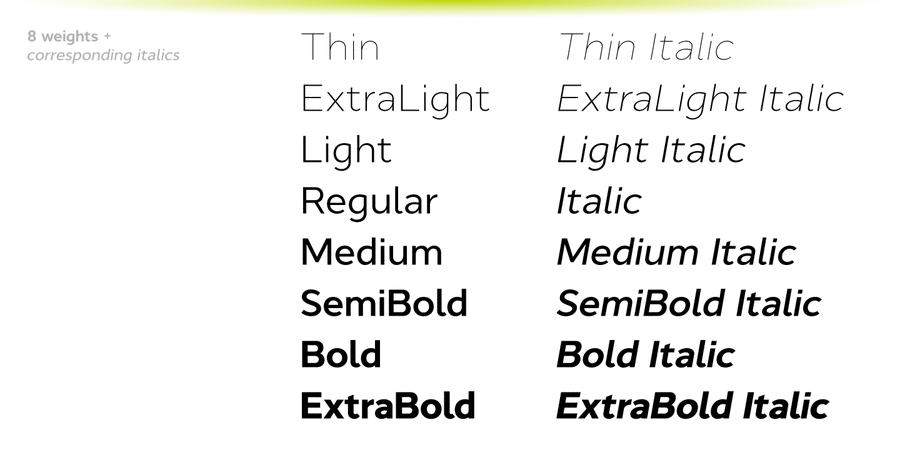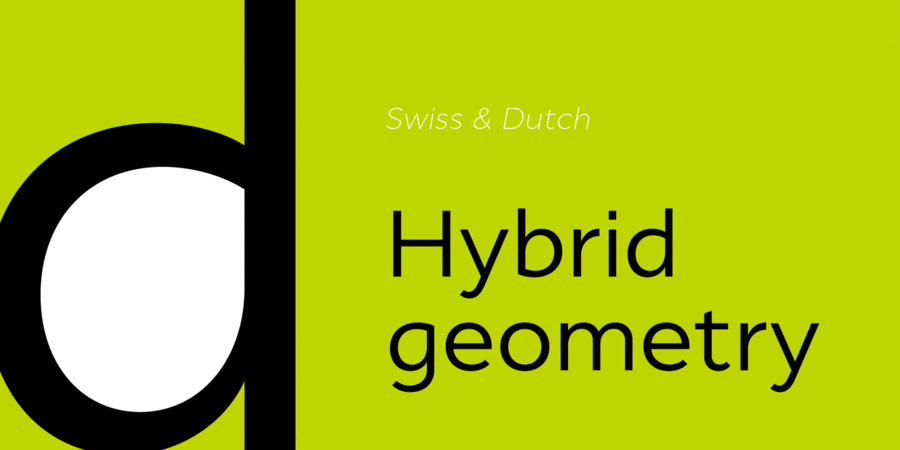
Cyntho Next – це сучасний геометричний шрифт без зарубок, в основі якого гібридна краплеподібна контрформа. Має 8 накреслень від тонкого до наджирного, включаючи кирилицю, а також численні OpenType-фічи.
Cyntho Next був повністю перероблений на основі нашого бестселера Cyntho Pro. Також є аналогічний брусковий шрифт – Cyntho Next Slab.
Шрифт розробив Андрій Константинов в 2019 році.
Хіт 2010-х Схожий на шрифти з логотипів, ігор, фільмів:
СТБ, Discovery Channel
Асоціації з сімейством шрифтів Cyntho NextОсобистість і характер гарнітури:
мінімалістичний, чіткий, делікатний, чистий, легкий, прохолодний, свіжий, модний, тонкий, сучасний, лаконічний, ясний, рівний, якісний, невагомий, прозорий, логічний, точний, повітряний, скляний, дротяний, міський, статичний, популярний, худий, глобалізований, глобалістічний, крихкий, холодний, Простий, твердий, зрозумілий, доступний, елементарний, правильний, формальний, серйозний, стійкий, стабільний, самостійний, відповідальний, західний, діловий, спокійний, креслярський, інженерний, нейтральний, помірний, стандартний, невиразний, універсальний, розумний, байдужий, комфортний, зручний, непомітний, ввічливий, обов'язковий, сильний, переконливий, урбаністичний, надійний, значний, солідний, важкий, важливий, мотивуючий, залізний, сталевий, грубий, впевнений, потужний, строковий, наполегливий
парфумерія, туалетна вода, шампунь, косметика, мода, інновації, дієта, дизайн, гігієна, чистота, Місто, прилад, суспільство, аеропорт, метро, навігація, архітектура, наука, одяг, реклама, магазин, медицина, взуття, креслення, інженер, математика, вода, транспорт, ліки, бізнес, торгівля, конструктор, гроші, банкнота, коворкінг, освіта, техніка, монета, хімія, фізика, урбаністика, Зубна паста, новини, автобус, технології, аптека, інструмент, верстат, паливо, енергетика, сталевар, мотор, двигун, вантажівка, далекобійник, промисловість, будівництво Гарнітура має ознаки стилів: